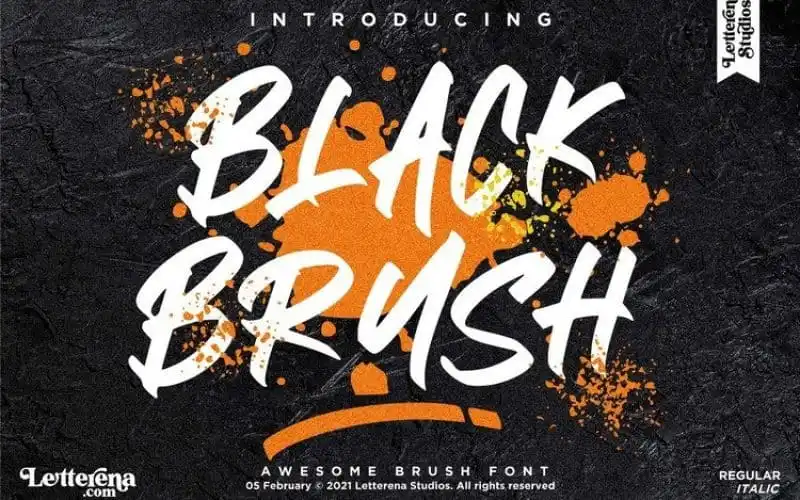
Black Brush Script Font – Fonte Grátis
Black Brush Script Font
A Black Brush Script Font é uma fonte escrita a mão rápida criada pela Letterena Studios. Ela é produzida usando um pen com forma de pincel e depois refinada para resultados suaves e equilibrados, tornando-a ideal para uma ampla gama de projetos. Esta inclui logomarcas, trabalhos de marcação, design de casa, embalagens de produtos, tigelas, citações, cartazes, sacolas de shopping, camisetas, capas de livros, cartões de nome, convites de aniversário, cartões de agradecimento, rótulos, fotografia e até eventos especiais. A Black Brush Script é perfeitamente adaptada para aqueles projetos que exigem um sabor forte do pincel, seja em sua forma mais sofisticada ou em um projeto mais luxuoso.